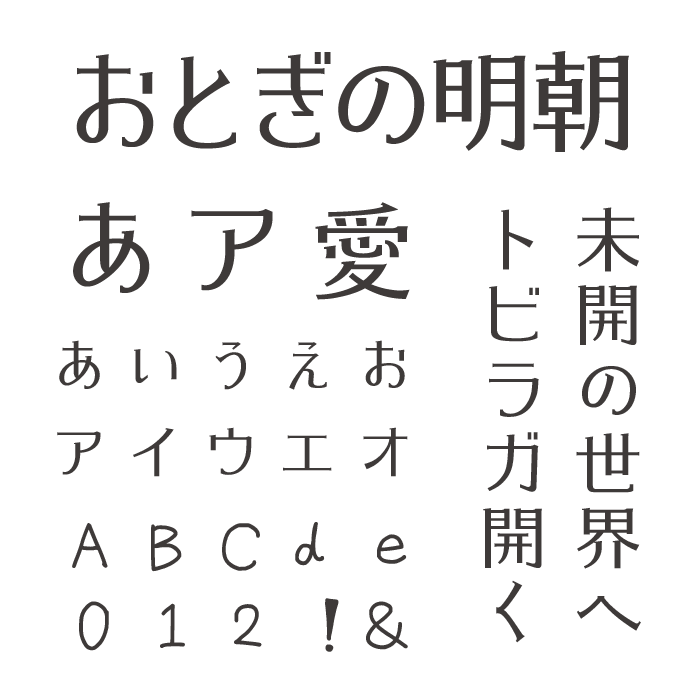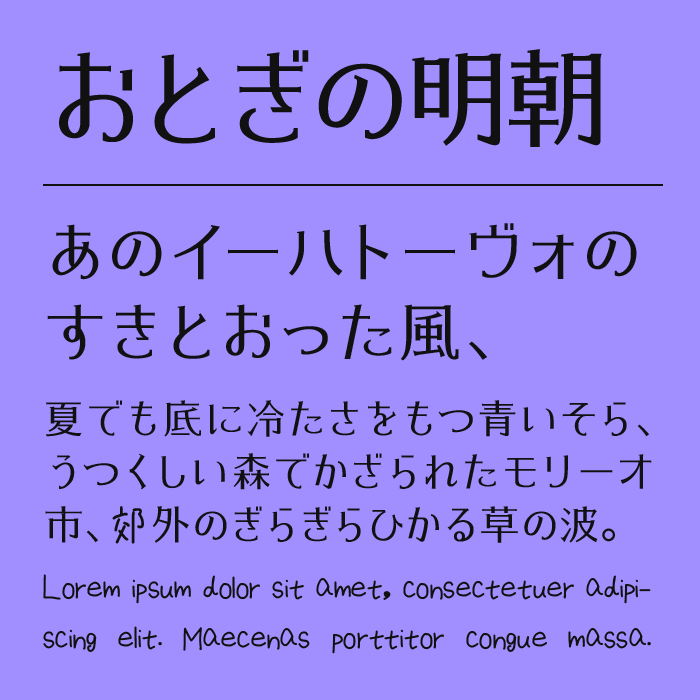
おとぎの明朝フォントは、クラシカルな明朝体をベースにしながら、柔らかな曲線や細かな抑揚によって物語性を感じさせるフォントです。
繊細な横画と凛とした縦画のバランスが美しく、どこか文学的で落ち着いた雰囲気を感じる明朝体です。派手な装飾に頼らず、文字そのものの品の良さで世界観を作り上げているフォントです。
童話や幻想文学を思わせる空気感があり、書籍のタイトルや詩的なビジュアル、和風デザインなどと特に相性が良いです。
読み進めるほどに静かな余韻が残り、画面全体に奥行きを与えてくれます。上品さと優しさを兼ね備えた、物語の入口のような魅力を持つフォントです。